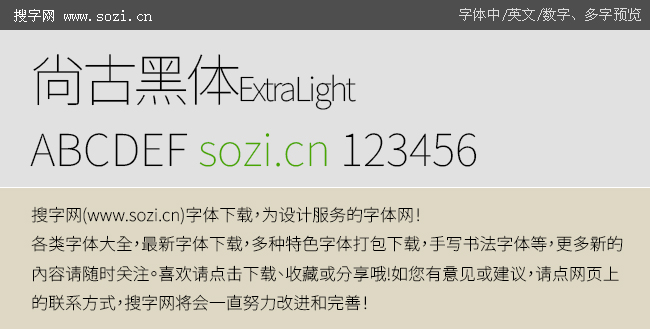
尚古黑體ExtraLight
搜字網提供一款尚古黑體ExtraLight中文字體下載,尚古字體是一套泛中日韓傳承字形(舊字形),基于思源黑體、思源宋體、思源等寬以及思源系列衍生字型制作,包含黑體、明體、圓體、等寬以及簡轉繁字型。這款字體無論是個人還是企業都可以自由免費商用,無需知會或者標明原作者。適合包裝設計、海報設計、廣告設計等應用。